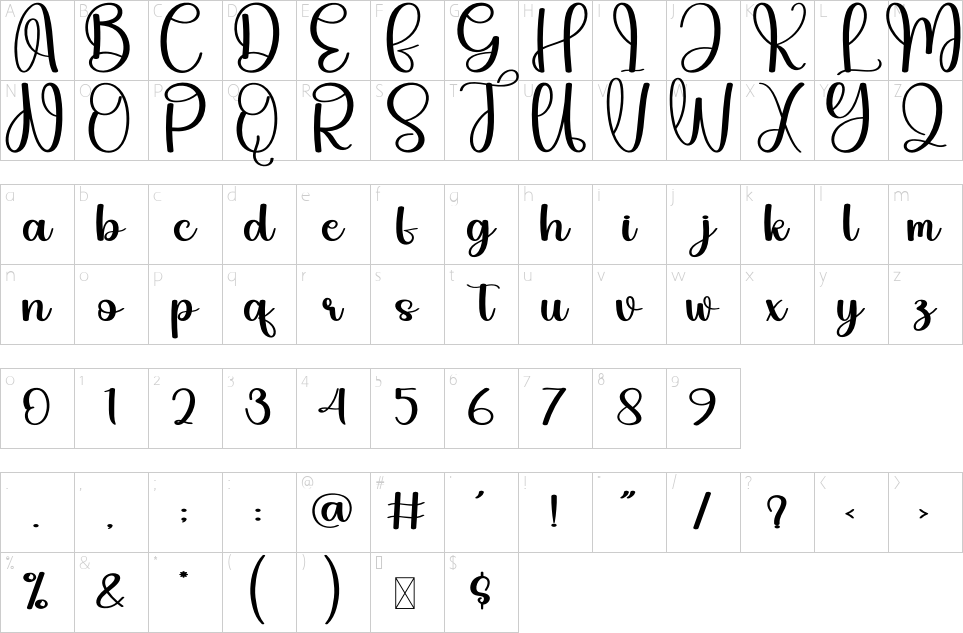
A Jellyfish font é uma fonte gráfica lúdica e enérgica, ideal para aqueles que buscam algo desconcertantemente alegre para suas criações digitais. Desenhada por um artista desconhecido, essa fonte traz à tona uma série de traços vivos e alegres, com uma aparência vibrante e fluida. Ela é perfeita para adicionar um toque de diversão em sites, redes sociais ou até mesmo para criar cartazes interativos. Com seu design único, a Jellyfish font oferece um contraste agradável e pode ser usada em diversos formatos para garantir que seu projeto tenha um ar descontraído e engraçado. Seja para aplicativos, sites ou qualquer outro tipo de conteúdo digital, essa fonte é uma ótima escolha para aqueles que desejam um toque alegre e descontraído em seu trabalho.